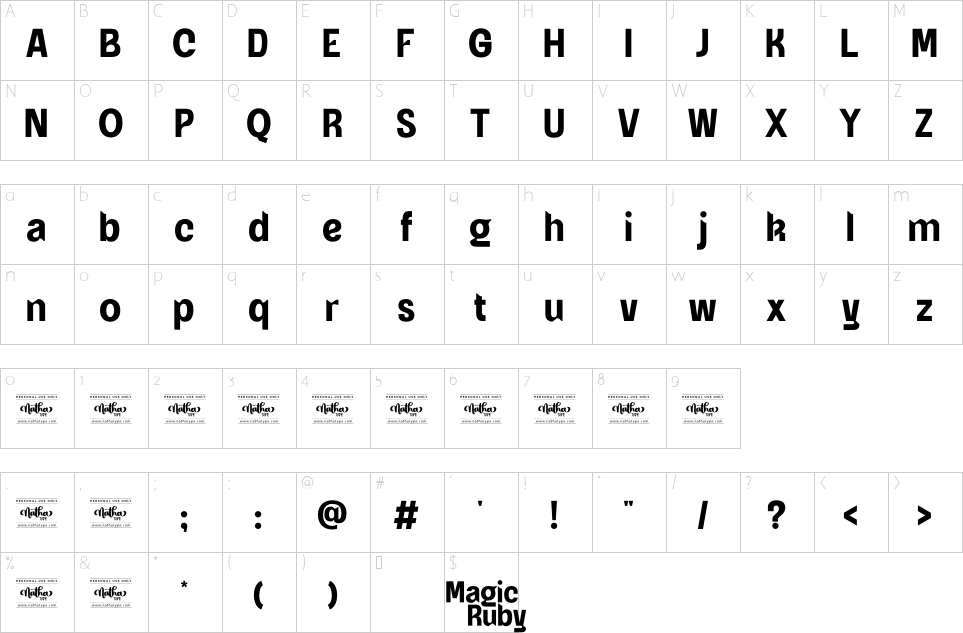
Descubra a magia da Magic Ruby font no site de 1001 Free Fonts, uma fonte gratuita para Windows e Mac. Desenhada pelo designer Natha Type, esta fonte única oferece uma mistura de elegância e sofisticação que complementará com perfeição qualquer projeto. Com um design que combina modernidade e tradição, Magic Ruby é perfeita para qualquer aplicação visual. Com seu download quebrando a marca dos 1.074, é evidente que a comunidade de designers e criadores de conteúdo já reconheceu a qualidade e versatilidade desta fonte. Se você está buscando uma fonte para dar um toque especial a seu próximo projeto, a Magic Ruby é uma excelente escolha. Comece seu design com Magic Ruby e descubra a magia em seu próprio estilo.